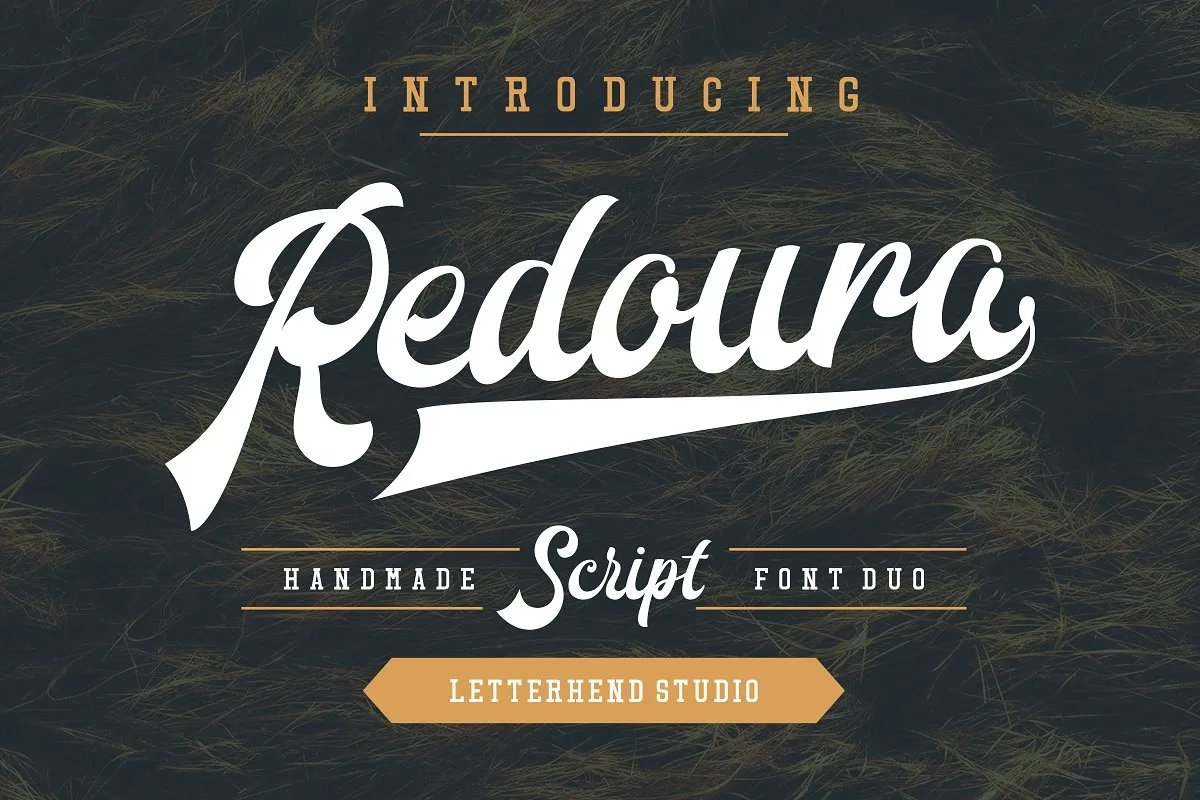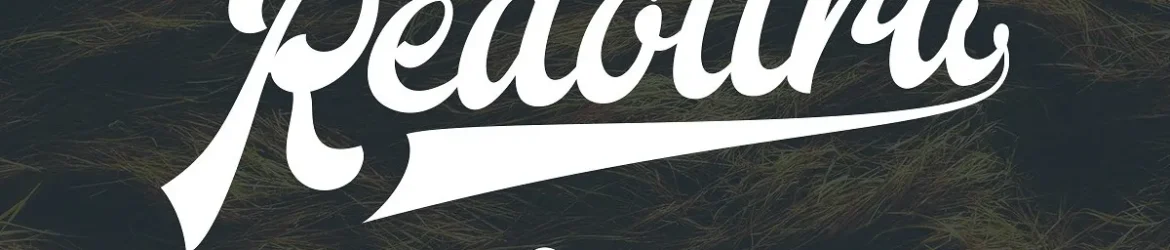
Descubra a beleza do Redoura Font Duo, uma fonte script inspirada nos estilos das fontes dos anos 70 e Script Sports. Especialmente adequado para logos de temas esportivos, esta fonte é um lançamento inovador da designer 178-MC. Redoura é uma tipografia de estilo script que incorpora tanto a versão serifada quanto o seu antigo e sofisticado irmão sans-serif. A dualidade desta fonte permite-lhe criar design gráfico único, combinando a elegância da tipografia serifada com o modernismo do tipo linhas. O Redoura Font Duo não apenas traz você de volta ao encanto dos anos 70, mas também oferece uma versão serifada perfeita para ser usada em combinação. Este conjunto inclui caracteres maiúsculos e minúsculos, sinais gráficos, números e suporta vários idiomas. Além disso, a fonte conta com alternativas e ligações de open type que permitem ainda mais flexibilidade na utilização. Não perca esta oportunidade única para adicionar um toque único e sofisticado às suas identidades digitais, seja ela em logotipos corporativos ou em websites. O Redoura Font Duo é uma ótima escolha para quem procura um tipo de letra que transmite elegância e modernidade ao mesmo tempo.